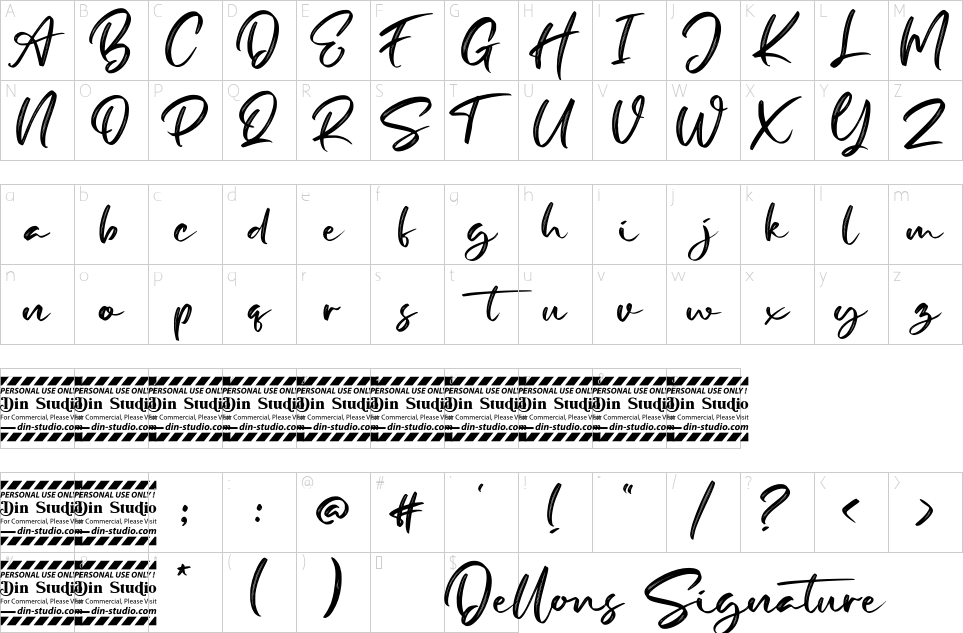
A Dellons Signature é uma elegante e sofisticada fonte que se destaca entre outras opções de letras gratuitas. Desenvolvida pela Din Studio, essa fonte incorpora elementos arquitetônicos modernos com um toque minimalista perfeito para criar textos chamativos e impactantes. Seu design curvilíneo e detalhes sofisticados tornam a Dellons Signature Font uma escolha versátil que se adapta bem tanto em aplicativos de escrita quanto em projetos digitais. Com apenas 2,711 downloads, você é um dos usuários especiais que escolheram essa fonte para dar um toque único ao seu trabalho. Seja para criar cartazes profissionais ou uma simples mensagem digital, a Dellons Signature está aqui para ajudá-lo a destacar-se. Descubra hoje e faça o download da sua versão.